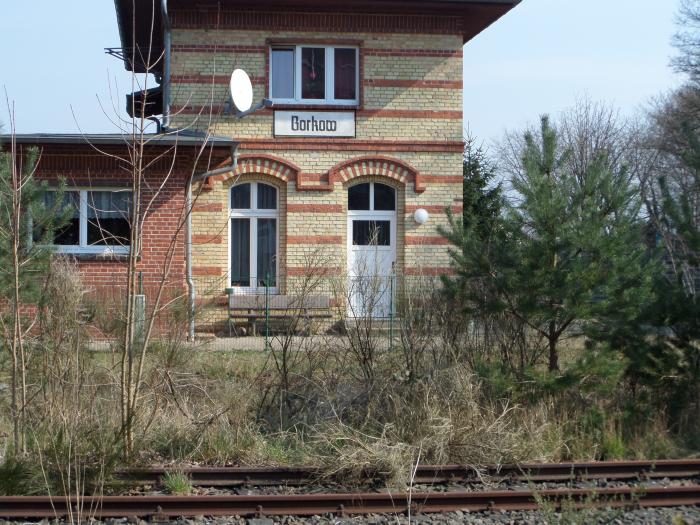
Eisenbahn Stationschild Borkow
Und diese Ortsschilder waren eben jeweils vom örtlichen Schildermaler von Hand geschrieben, was ja gerde der Vorteil dieser schlichten frakturschriften war, sie waren von jeden, der weinen geraden Strich malen konnte auch gut lesbar umzusetzen. das führt allerdings dazu, dass man kaum eine 100% zur jeweiligen Beschiftung passnde digitale Schrift finden wird, obwohl dem Bahnreisenden die Beschrifdtung dann - da ja eine direkte Vergleichbarkeit fehlt - als überall gleich empfunden wird.